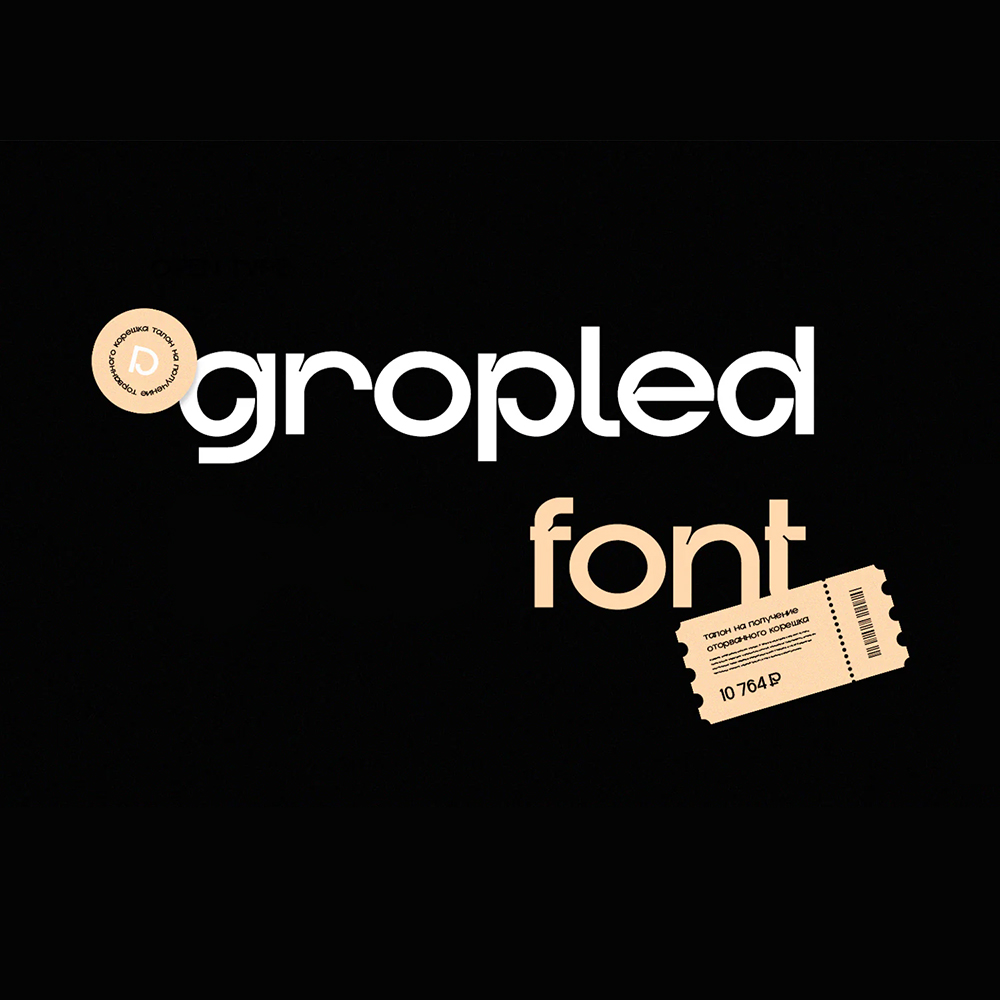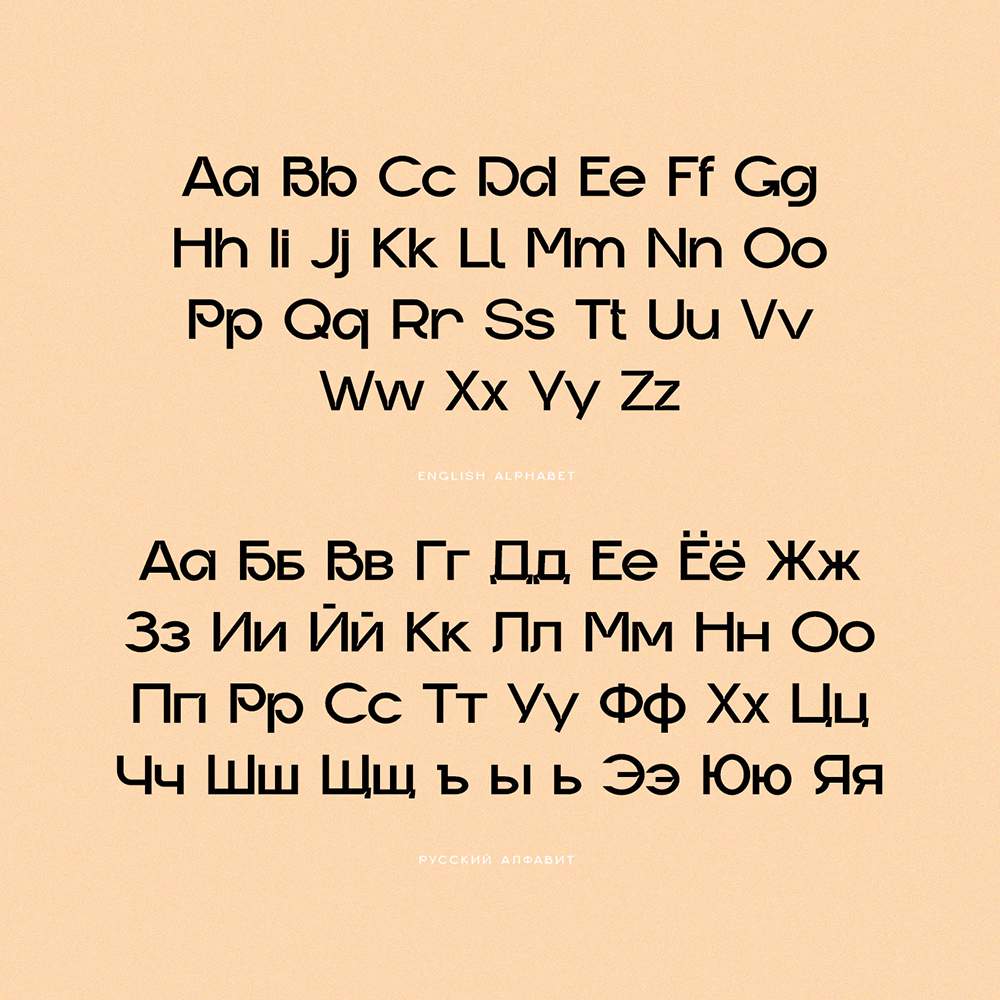
فونت پرمیوم و انگلیسی Gropled Font یک فونت نمایشی مدرن است و با تلههای جوهر منحصر به فرد و منحنیهای باز خود مشخص میشود. این فونت برای…
فونت پرمیوم و انگلیسی Gropled Font یک فونت نمایشی مدرن است و با تلههای جوهر منحصر به فرد و منحنیهای باز خود مشخص میشود. این فونت برای انواع پروژههای طراحی، از جمله برندسازی، لوگو، طراحی وب و مواد تبلیغاتی مناسب است. ساختار هندسی این فونت خوانایی بالایی را تضمین میکند و آن را برای کاربردهای نمایشی و متنی ایدهآل میسازد و آن را به انتخابی همهکاره برای طراحانی تبدیل میکند که به دنبال بهبود پروژههای خلاقانه خود هستند.